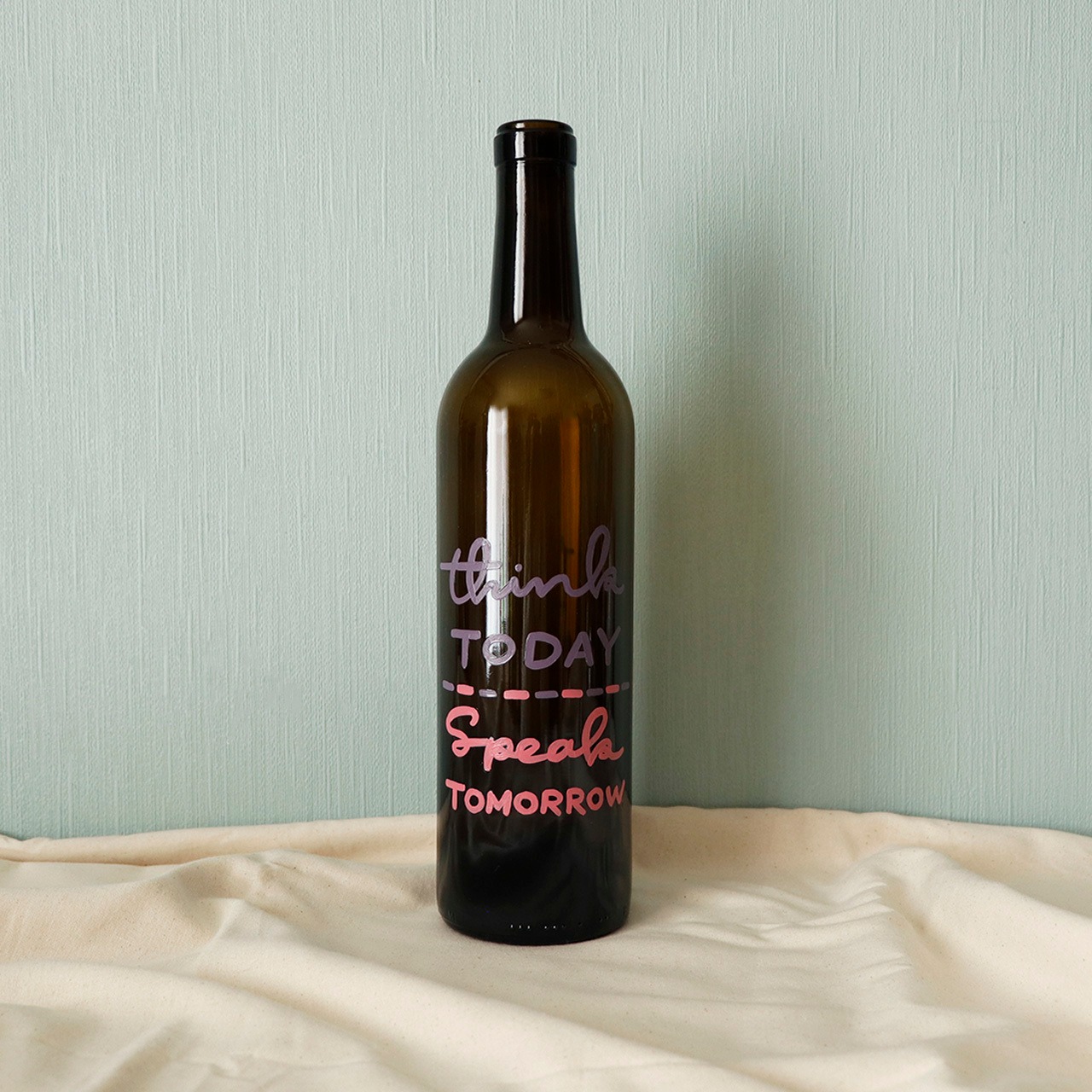
【BOTTLE PAINT ART】Think Today,Speak Tomorrow
ワインのボトルにペイントした、気軽に飾れるアートな作品が登場!
Think Today,Speak Tomorrow
今日は考えて、明日話そう
よくよく考えてから物事を話さないといけない場面ってたくさんありますよね。
自分を落ち着かせるためにも、そばにこの言葉を。。。
デザインはあえてポップに仕上げました。
光が入るとこに置くと、瓶の色とともに文字も影になって素敵ですよ!!